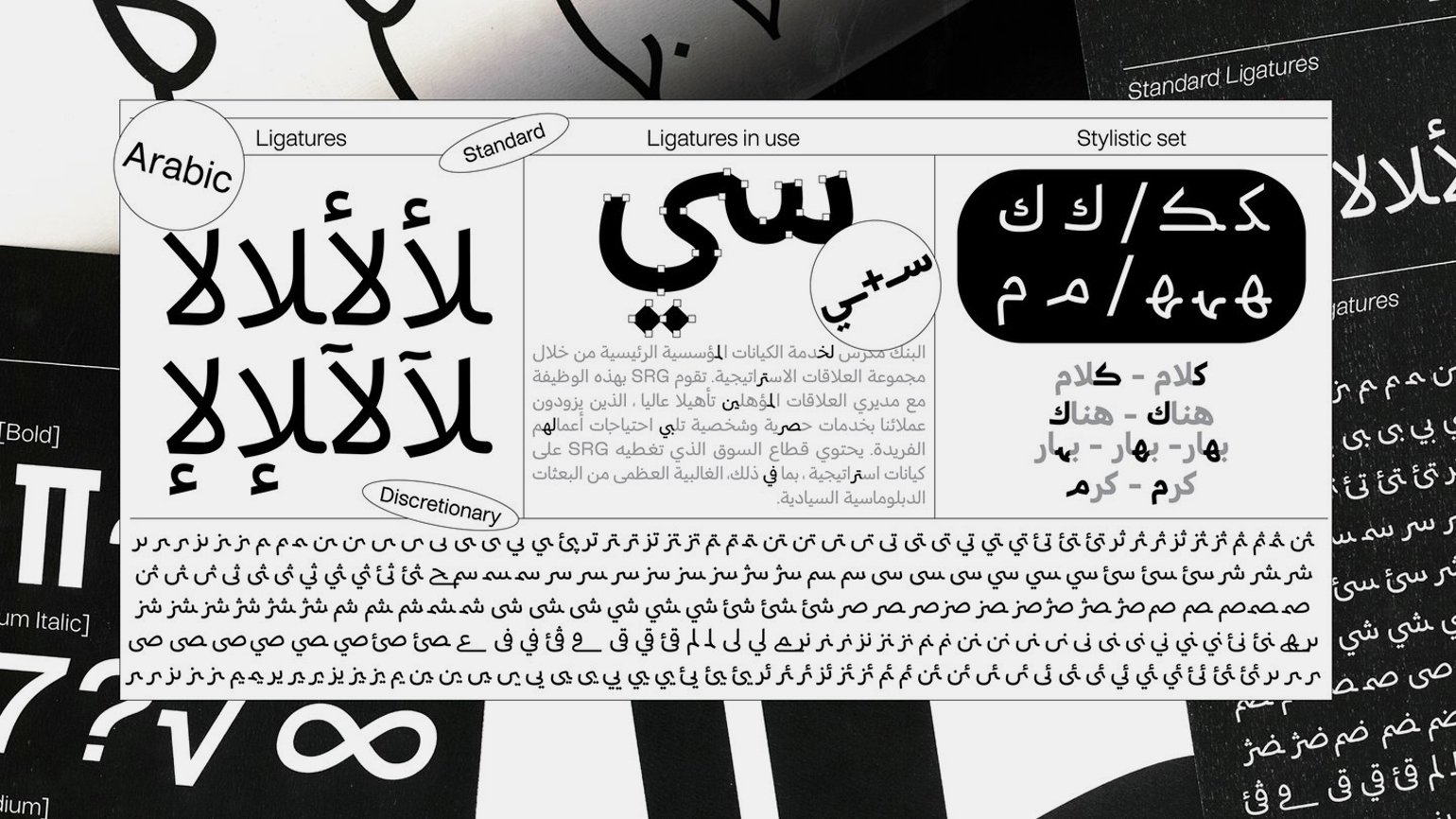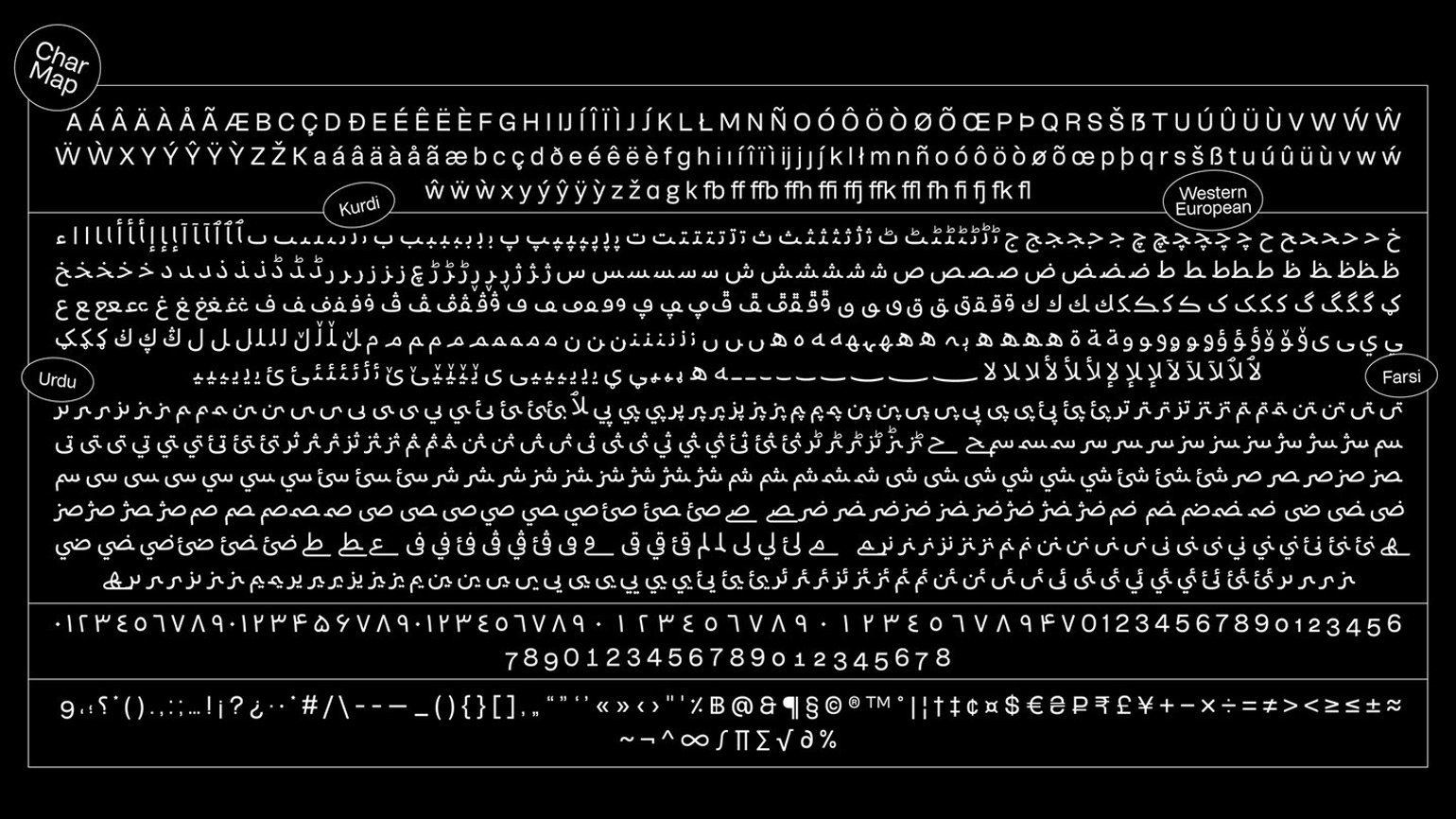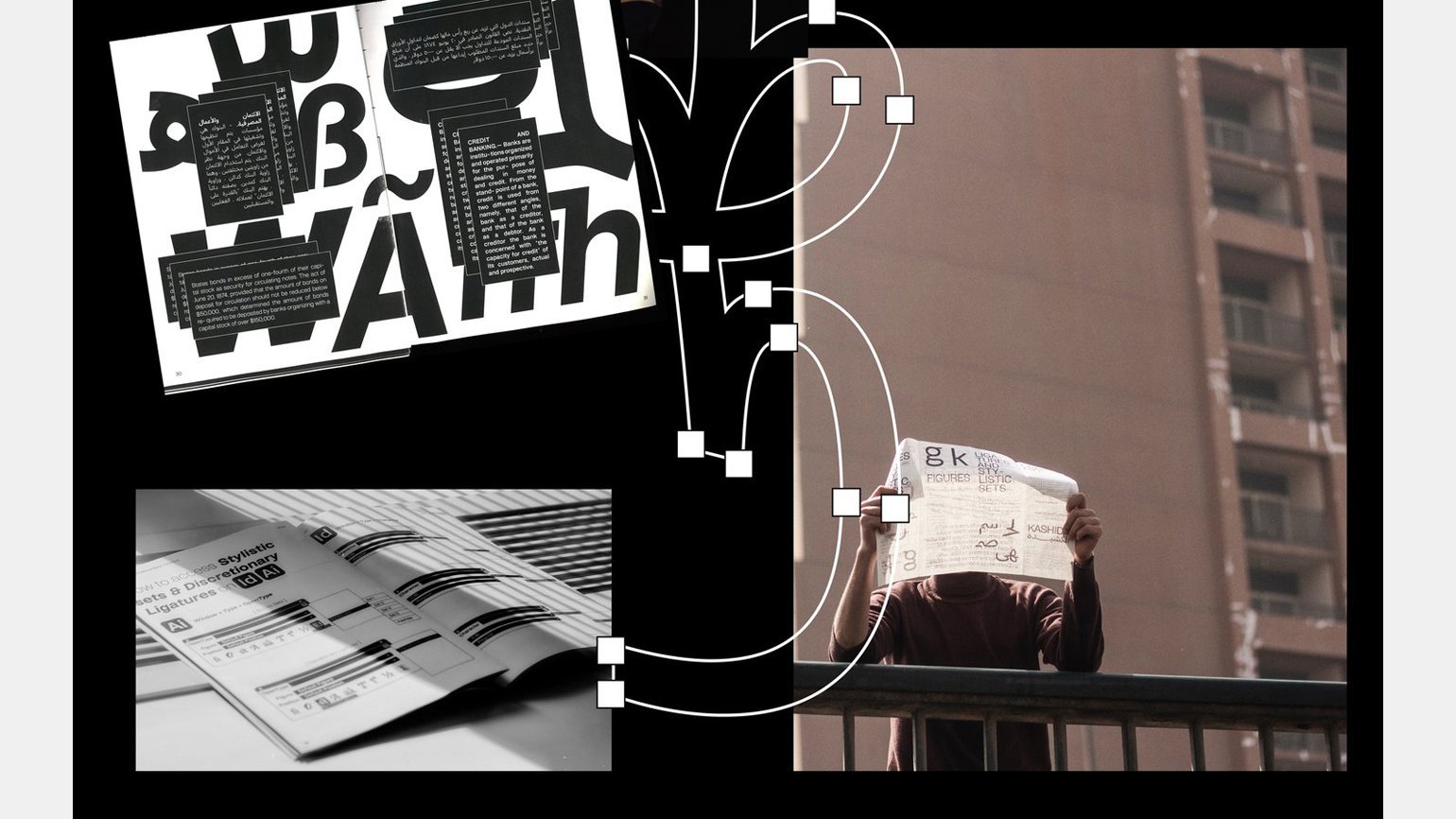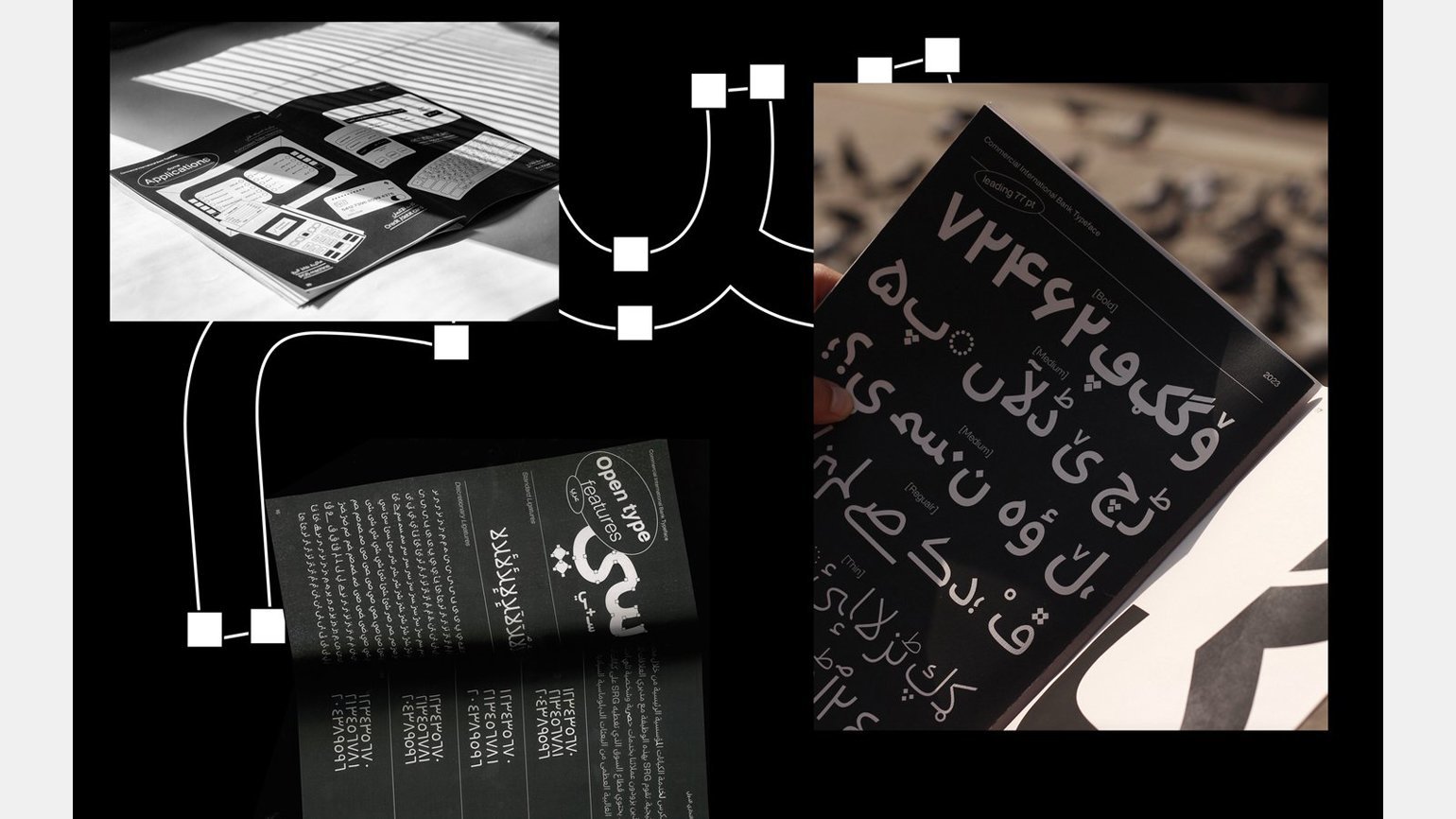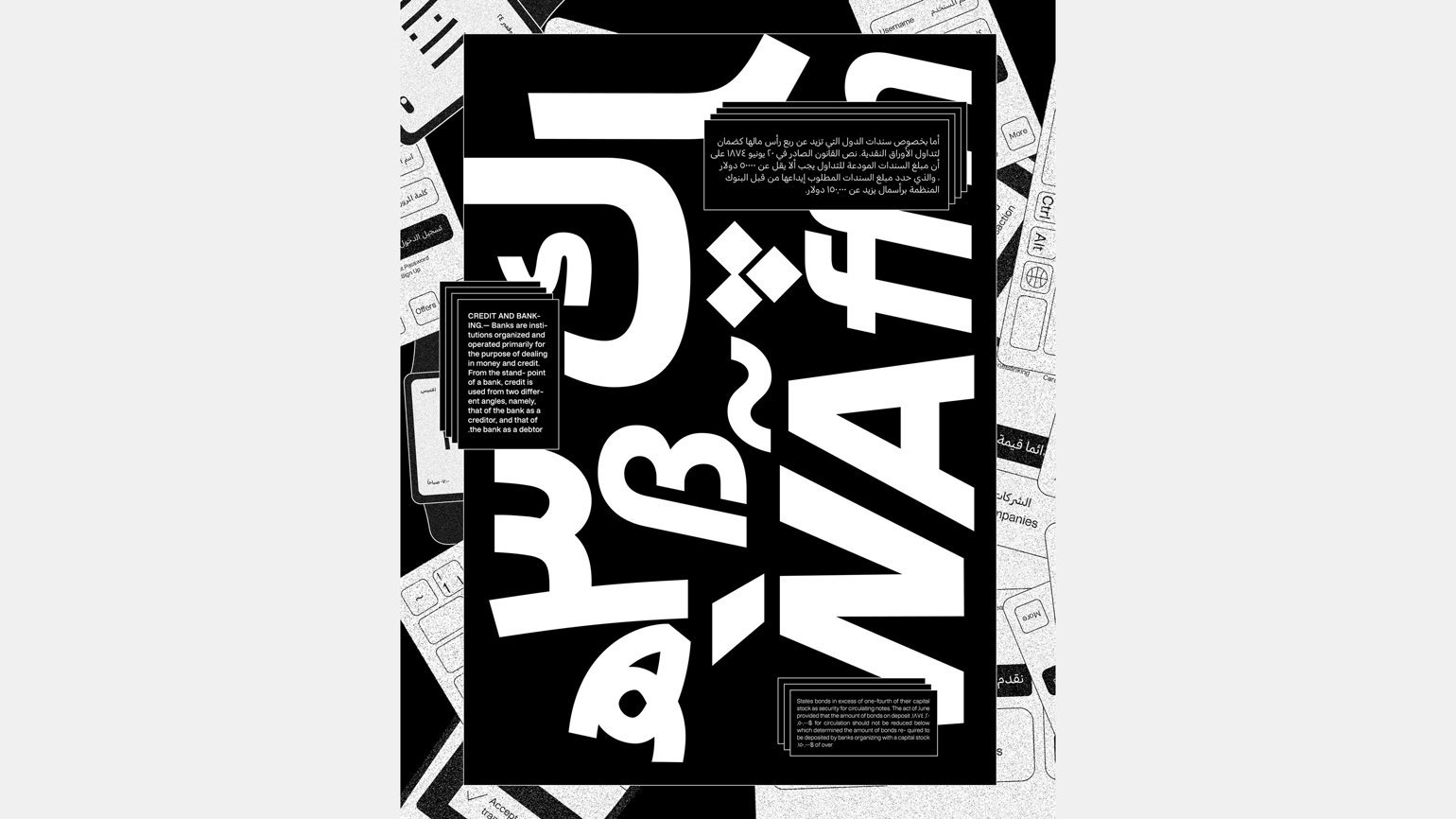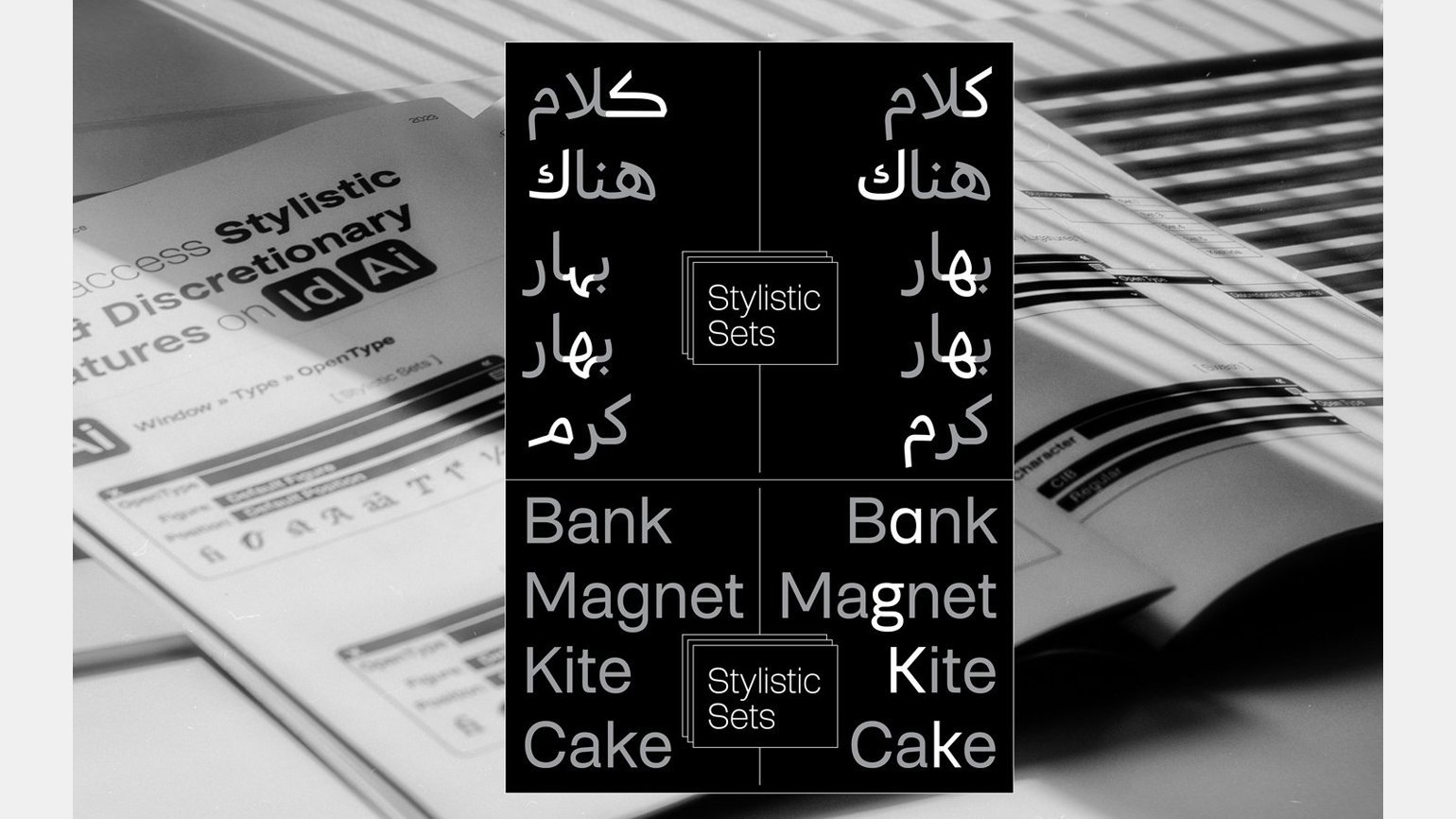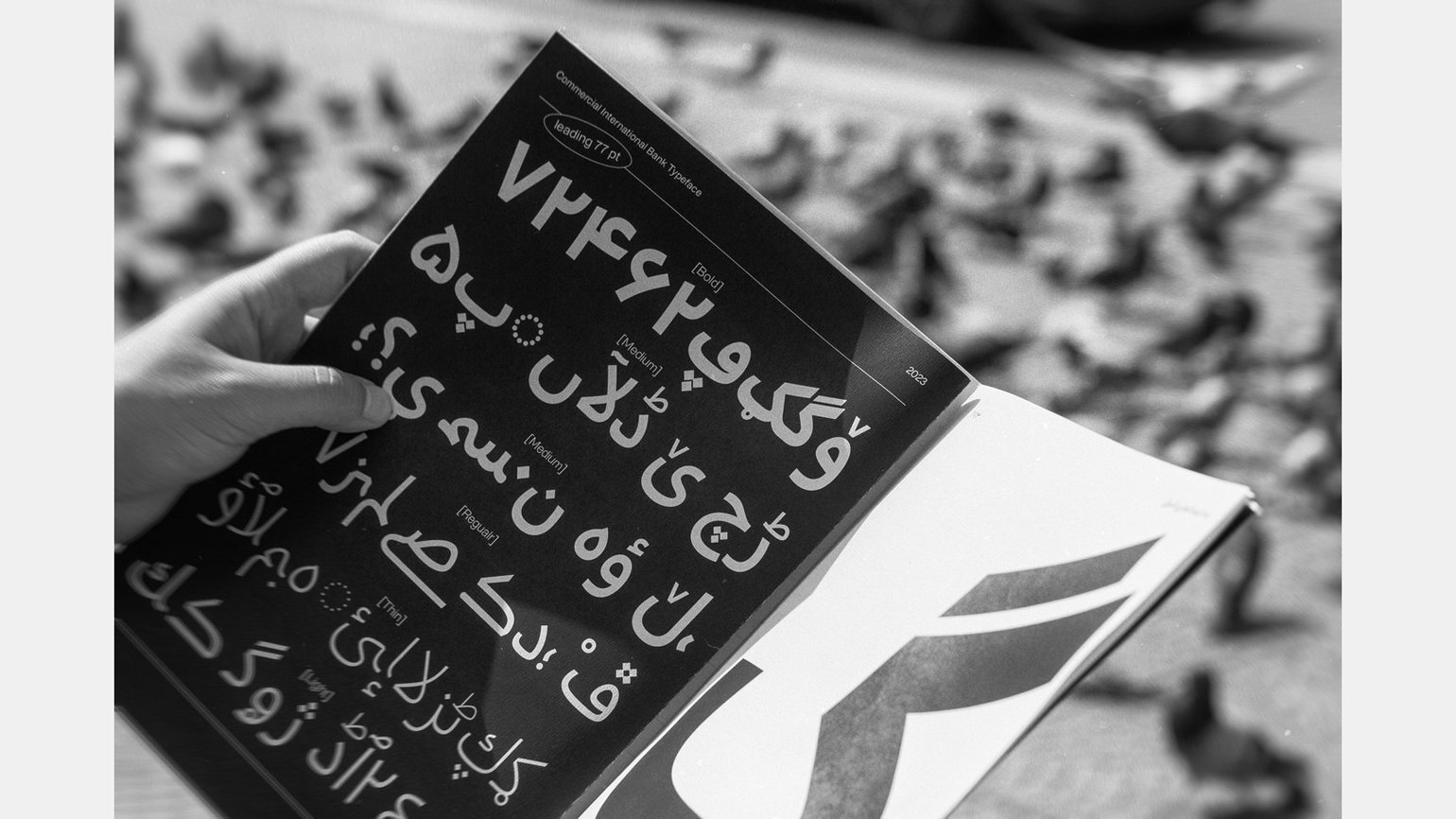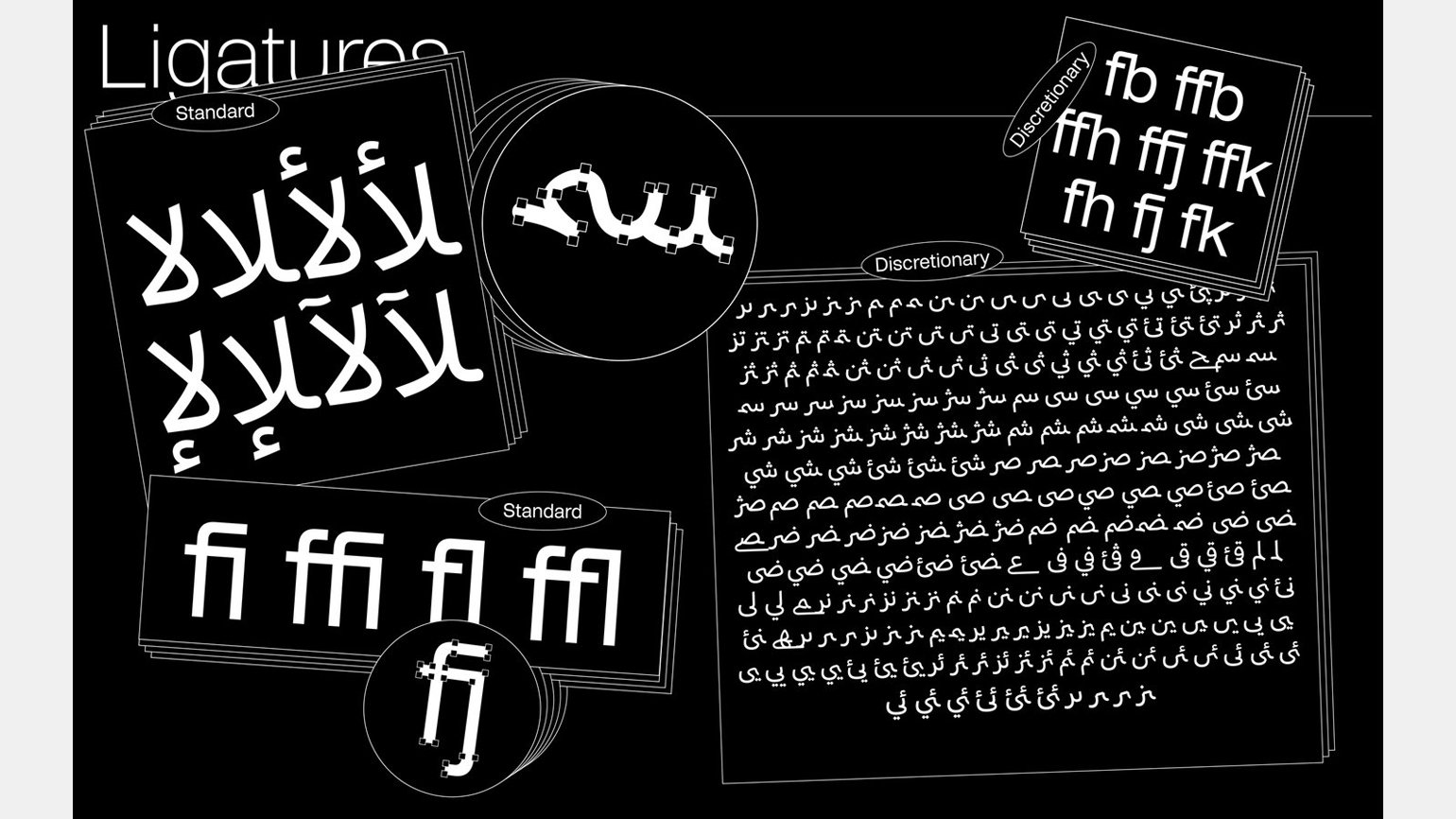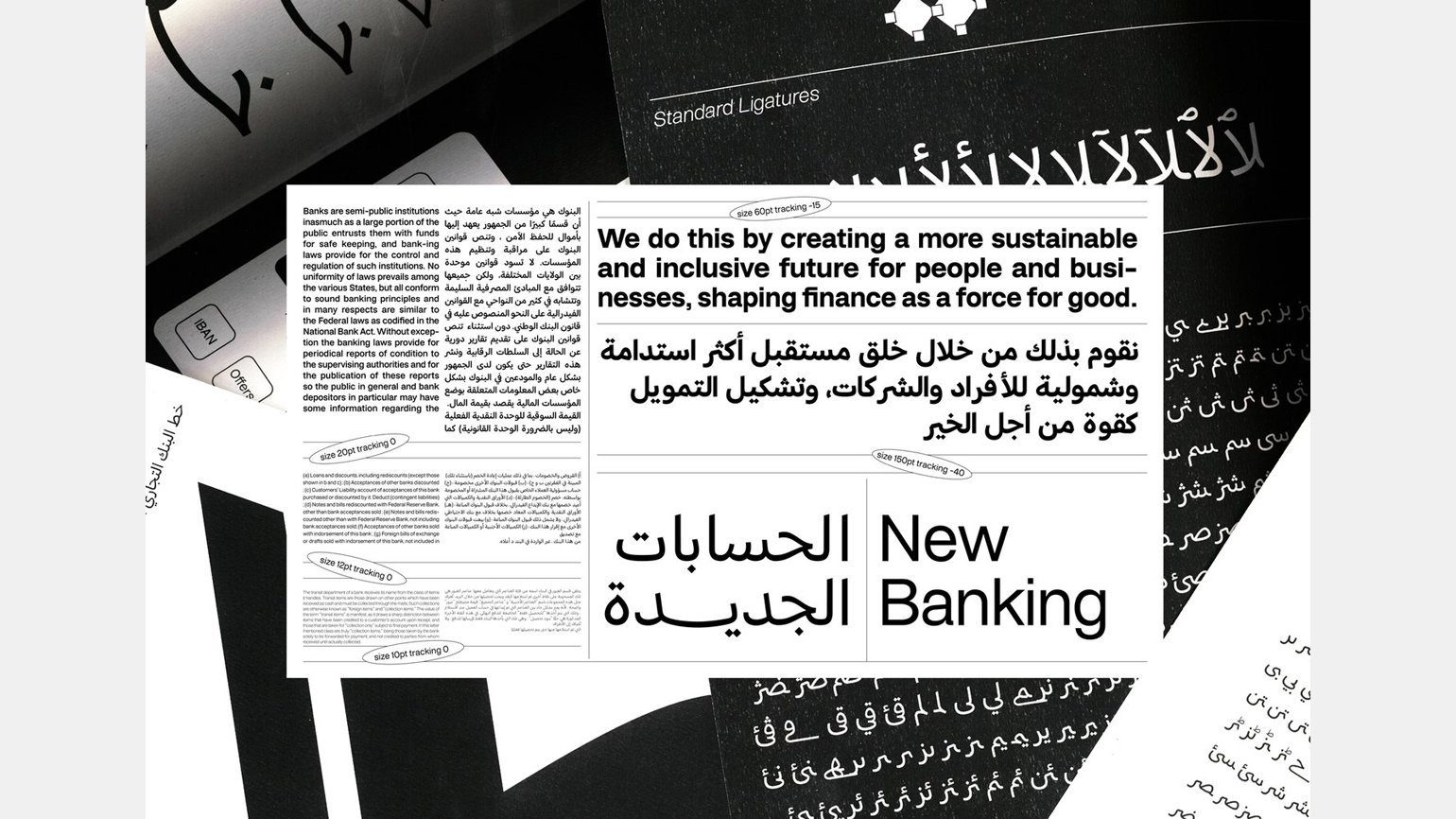
Шрифт для египетского банка CIB сделали по-настоящему двуязычным
Вместо того чтобы подстраивать арабскую вязь под латиницу, оба написания разрабатывали параллельно.
Ntsal, студия из Каира, и Boharat, литейная мастерская по производству арабских шрифтов, выпустили кастомный шрифт для египетского банка. Дизайнеры заменили предыдущую айдентику CIB, в которой арабский шрифт разработали на основе латинского, создавая две гарнитуры одновременно.
CIB Custom Typeface
«Отправной точкой в этом проекте было желание отдать предпочтение языку страны, в которой работает клиент, — в данном случае арабскому, — заявили в Ntsal. — Наше сотрудничество с Boharat Type Foundry включало в себя обширные исследования арабской типографики, особенно с точки зрения рисунка и пропорций букв».
CIB Custom Typeface
CIB Custom Typeface — это гротеск с несколькими весами для использования в разных ситуациях. Он поддерживает основные латинские и арабские символы, а также западноевропейские символы, урду и персидский язык. Стилистически он выполнен в начертании насх — это удобочитаемый эталон, используемый при наборе длинных абзацев на арабском языке. Одним из самых важных элементов для работы была кашида — тип курсивного выравнивания, используемый в арабском письме, при котором может быть удлинён текст, а не пробелы.
CIB Custom Typeface
Для Ntsal то, что банк вложился в разработку шрифта, говорит о многом: «Мы рады, больше людей в Египте узнают о возможностях шрифтового дизайна, — говорят в студии. — Кастомный шрифт предлагает прекрасную возможность как для дизайнеров, так и для брендов подчеркнуть тональность бренда в различных каналах коммуникации».
CIB Custom Typeface